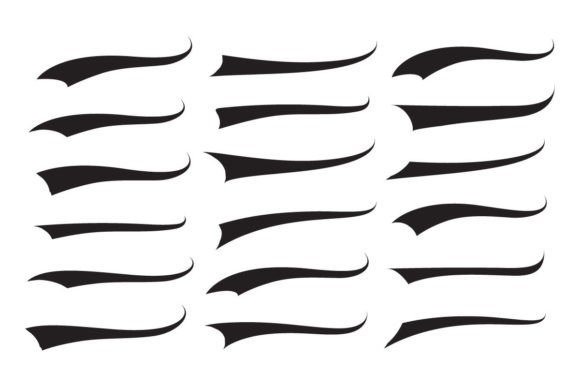
Font Swoosh Tails Ornamental Vector
Att hitta rätt designelement kan vara utmanande, men Font Swoosh Tails Ornamental Vector erbjuder en exceptionell samling som omedelbart lyfter ditt arbete.
Oavsett om du skapar POD-produkter (Print on Demand), bröllopsinbjudningar eller grafik för sociala medier, är Font Swoosh Tails Ornamental Vector ett perfekt val.
Experttips: Kombinera dessa element med kompletterande typsnitt för att skapa unika, iögonfallende mönster som sticker ut.